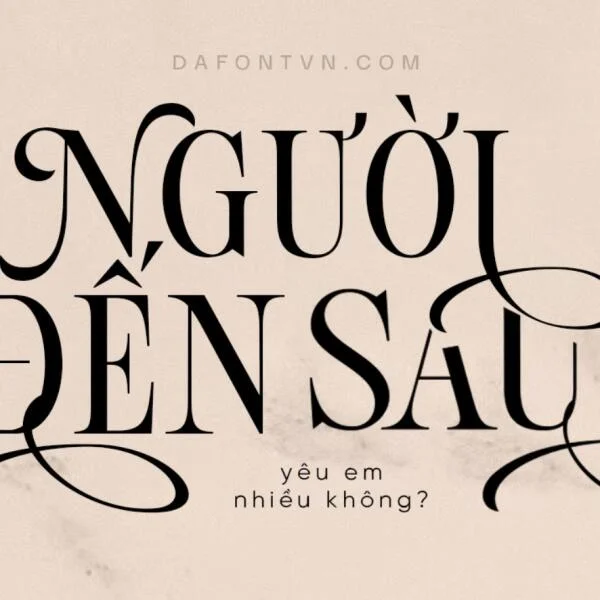
Tải Font Valky Việt hóa v2 - sự giao thoa giữa cổ điển và hiện đại
Font Valky là kiểu chữ có chân, được sáng tạo dựa trên sự giao thoa giữa cổ điển và hiện đại với thiết kế đẹp mắt. Đi kèm với font là rất nhiều glyph đặc biệt để thay thế giúp bạn dễ dàng tạo ra các thiết kế ấn tượng.
Tổng quan về Font Valky
Font Valky là kiểu chữ serif cổ điển nhưng cũng có 1 chút hiện đại lạ mắt với các chữ ghép đẹp, rất nhiều glyphs thay thế đặc biệt và hỗ trợ đa ngôn ngữ. Đây là một bộ phông chữ rất linh hoạt, hoạt động tuyệt vời ở các kích thước lớn và nhỏ.
Hoàn hảo cho các dự án biên tập, thiết kế logo, xây dựng thương hiệu, thời trang, quần áo, bao bì sản phẩm, tiêu đề tạp chí hoặc đơn giản là 1 kiểu font ấn tượng cho bất kỳ thiết kế nào.
Font Valky Việt hóa Preview 1
Mẫu 1
Font Valky Việt hóa Preview 2
Mẫu 2
Chi tiết các ký tự của Font Valky Việt hóa v2
Font được việt hóa 8 kiểu đầy đủ bởi NVN.
Chi tiết ký tự 1
Chi tiết ký tự 2
Chi tiết ký tự 3